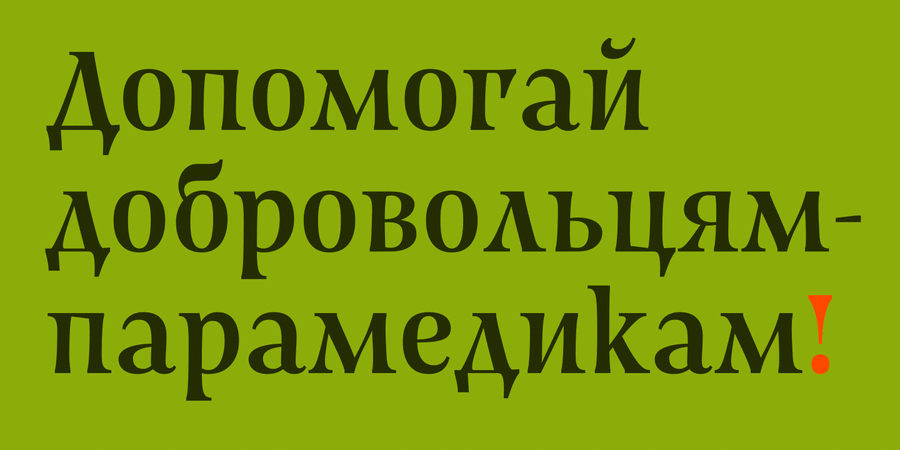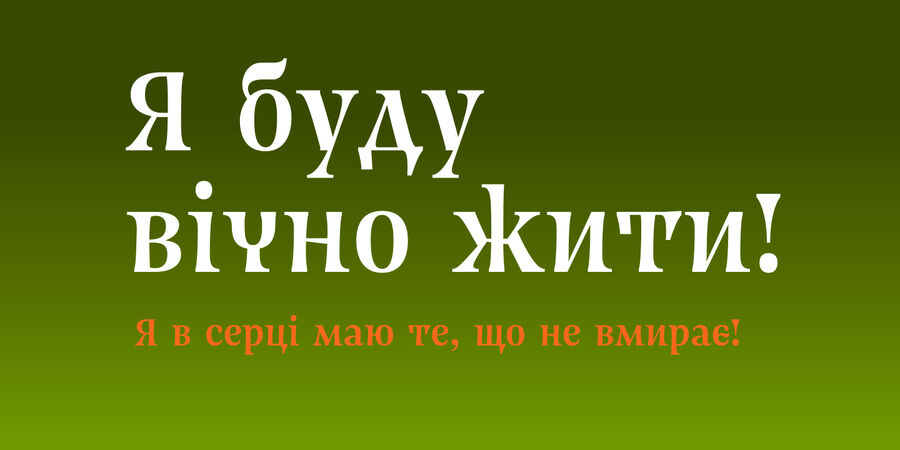
Чудовий пластичний взірець української перехідної антикви, що заповнює певну нішу в нашому доробку. Перехідна антиква – універсальний клас, що поєднує жвавість та певну каліграфічність ренесансної антикви з друкарською технічністю та впорядкованістю класицистичної нової антикви, й завдяки цьому має широке універсальне застосування від боді-тексту до реклами, логотипів тощо. Пропонований шрифт містить українську та англійську абетки та мінімальний необхідний набір допоміжних ґліфів, але при потребі можна замовити розширення ґарнітури у будь-який бік: за жирністю, нахилом, шириною, абетковим та мовним складом тощо. Шрифт розробив Андрій Шевченко у 2022 році.
Асоціації з сімейством шрифтів MavkaОсобистість і характер гарнітури:
красивий, виразний, характерний, майстерний, легендарний, благородний, прекрасний, художній, динамічний, аристократичний, старомодний, старовинний, історичний, казковий, лицарський, святковий, пивний, фантастичний, племінний, пластичний, урочистий, ввічливий, культурний, гармонійний, чистий, свіжий, ефектний, модний, якісний, добірний, елітний, дорогий, розкішний, елегантний, ювелірний, естетичний, витончений, знаменитий, дорогоцінний, оригінальний, багатий, яскравий, артистичний, гламурний, сексуальний, лісовий
епос, музей, меморіал, пам'ятник, прикраса, ювелір, надгробок, мистецтво, історія, ресторан, геральдика, казка, лицар, обладунки, сувій, одяг, тату, татуювання, король, дракон, фентезі, Чарівна казка, карти, гра, пиво, таверна, чай, свято, Christmas, паб, живопис, замок, банкнота, монета, сир, легенда, музика, квіти, краса, парфумерія, туалетна вода, шампунь, косметика, преміум, готель, шоколад, золото, коштовності, сервіровка, опера, розкіш, мода, театр, алкоголь, коньяк, бутік, гламур, Інстаграм, парфуми, люкс Гарнітура має ознаки стилів: